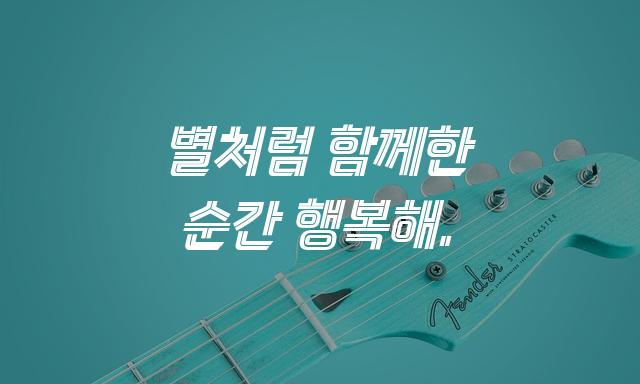
‘자이언츠체’는 (주)롯데자이언츠가 제작한 기본 고딕 폰트로, 이탤릭 스타일이 강조된 제목용 디자인입니다. 스포츠와 역동성을 담아낸 감성으로, 강렬하고 활동적인 분위기를 연출합니다.
자이언츠체은(는)
기본 고딕, 기울임, 감성적인, 게임 느낌, 부드러움, 길고/크고 계열의 생김새를 가지고 있으며
포스터, 광고 캠페인, 디지털 광고 등에서 자주 활용되며, 효과적인 메시지 전달에 적합합니다.
이 폰트는 광고/마케팅, 엔터테인먼트, 소매/유통 분야에 잘 어울리며,
창의적인, 강렬한, 재미있는 느낌을 담고 있는 것이 특징입니다.